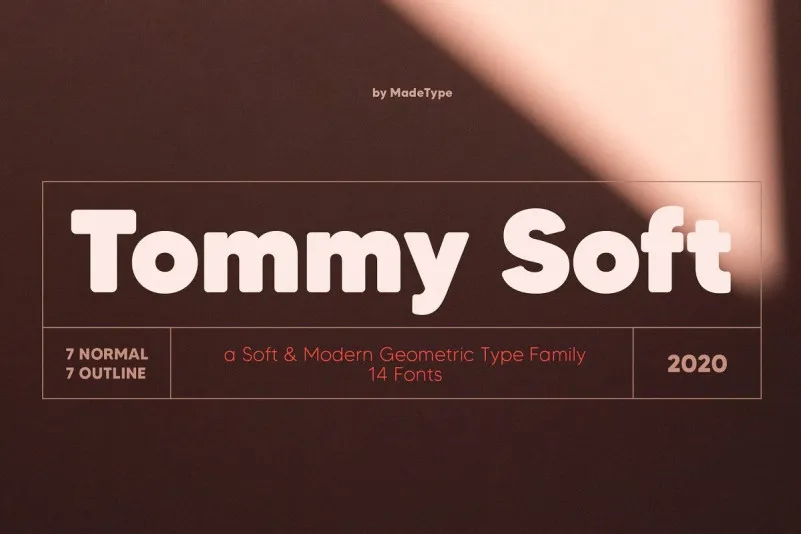
MADE Tommy Soft Font Family – Download Grátis
Aqui está uma descrição envolvente e natural para a página de download da font ‘MADE Tommy Soft Font Family’, no português do Brasil: Escolha a sua tipografia perfeita com ‘MADE Tommy Soft Font Family’. Esta é uma família geométrica de tipo moderna e suave, que incorpora tanto estilo clássico quanto elegância moderna. Com 7 fontes normais e 7 em formato linha leve, esta família de tipos é ideal para diversas aplicações, desde design fashion até editoriais e websites. A fonte ‘MADE Tommy Soft Font Family’ é perfeita para aqueles que buscam uma tipografia suave e moderna. Ela transmite um toque de sofisticação sem se perder no excesso, o que a torna ideal tanto para aplicações mais clássicas quanto para designs mais ousados. Seja para uma camiseta da moda ou uma revista fashion, para criar um logo minimalista ou um design de marca elegante, apostar em ‘MADE Tommy Soft Font Family’ é uma escolha que certamente deixará seu projeto atraente e único. Se você está buscando uma tipografia que combine a simplicidade geométrica com uma delicadeza moderna, esse é o tipo perfeito para você.